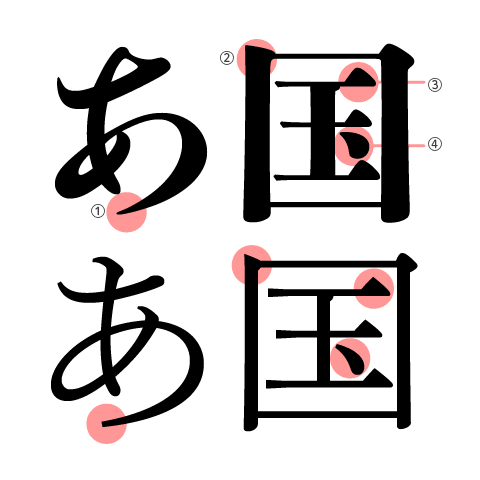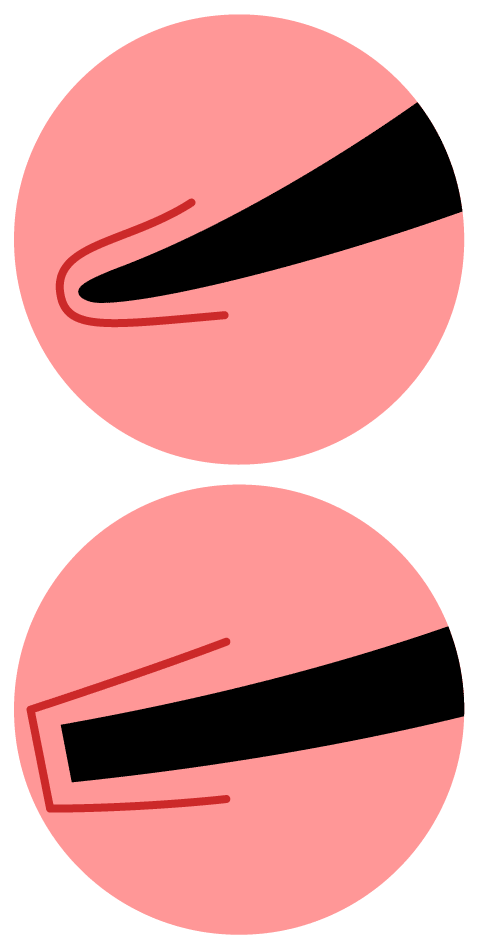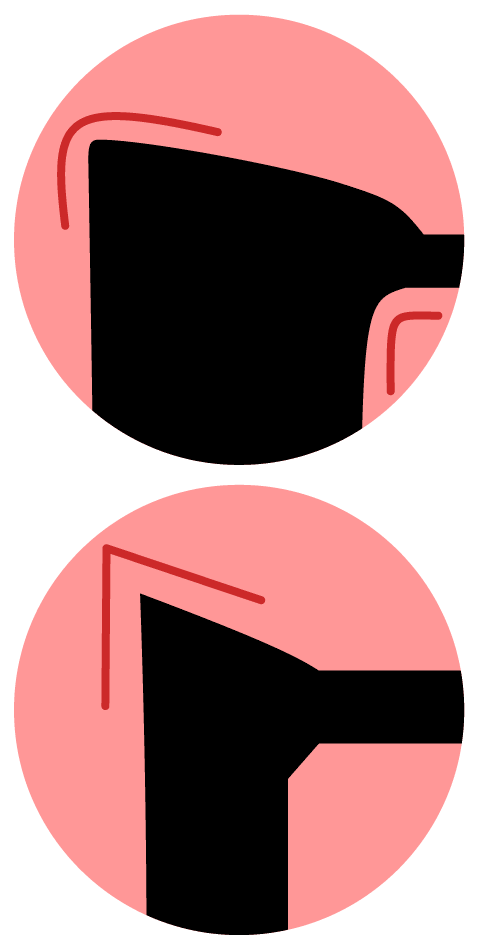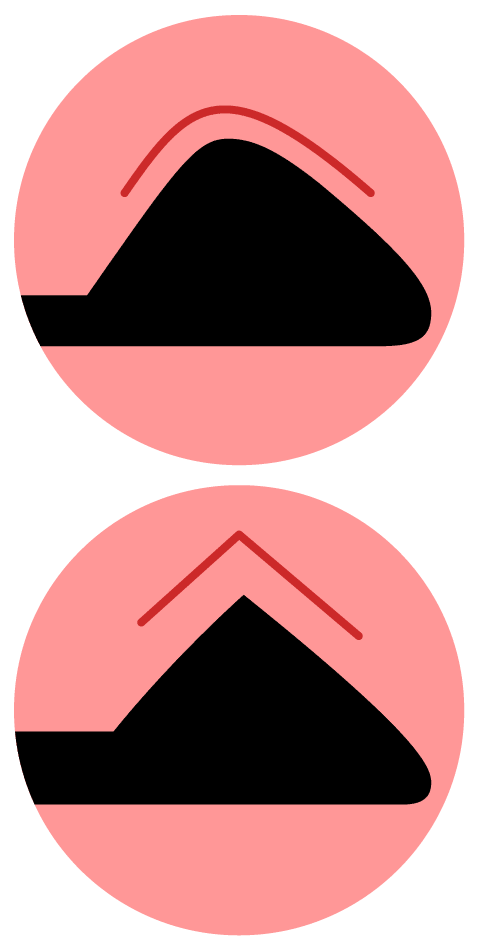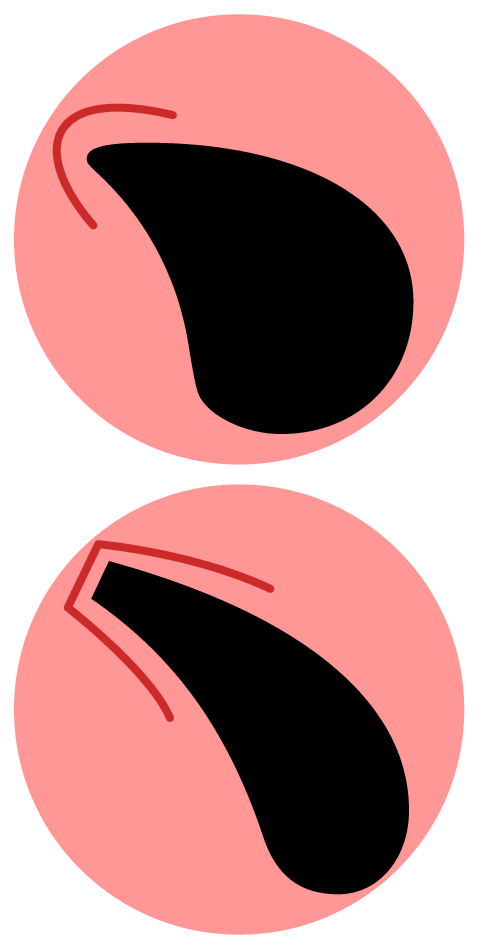
秀英初号明朝の特徴(拡大図)
初号明朝は、大サイズで使用したときに、角や先端が直線的にならないよう、柔らかく自然な印影で目に馴染むような形状に設計しています。プルっとした形を拡大図でご覧ください!
上:秀英初号明朝 下:秀英明朝L
1.ハライ 2.起筆 3.ウロコ 4.テン
1.ハライ
上:秀英初号明朝 下:秀英明朝L
2.起筆
上:秀英初号明朝 下:秀英明朝L
3.ウロコ
上:秀英初号明朝 下:秀英明朝L
4.テン
上:秀英初号明朝 下:秀英明朝L